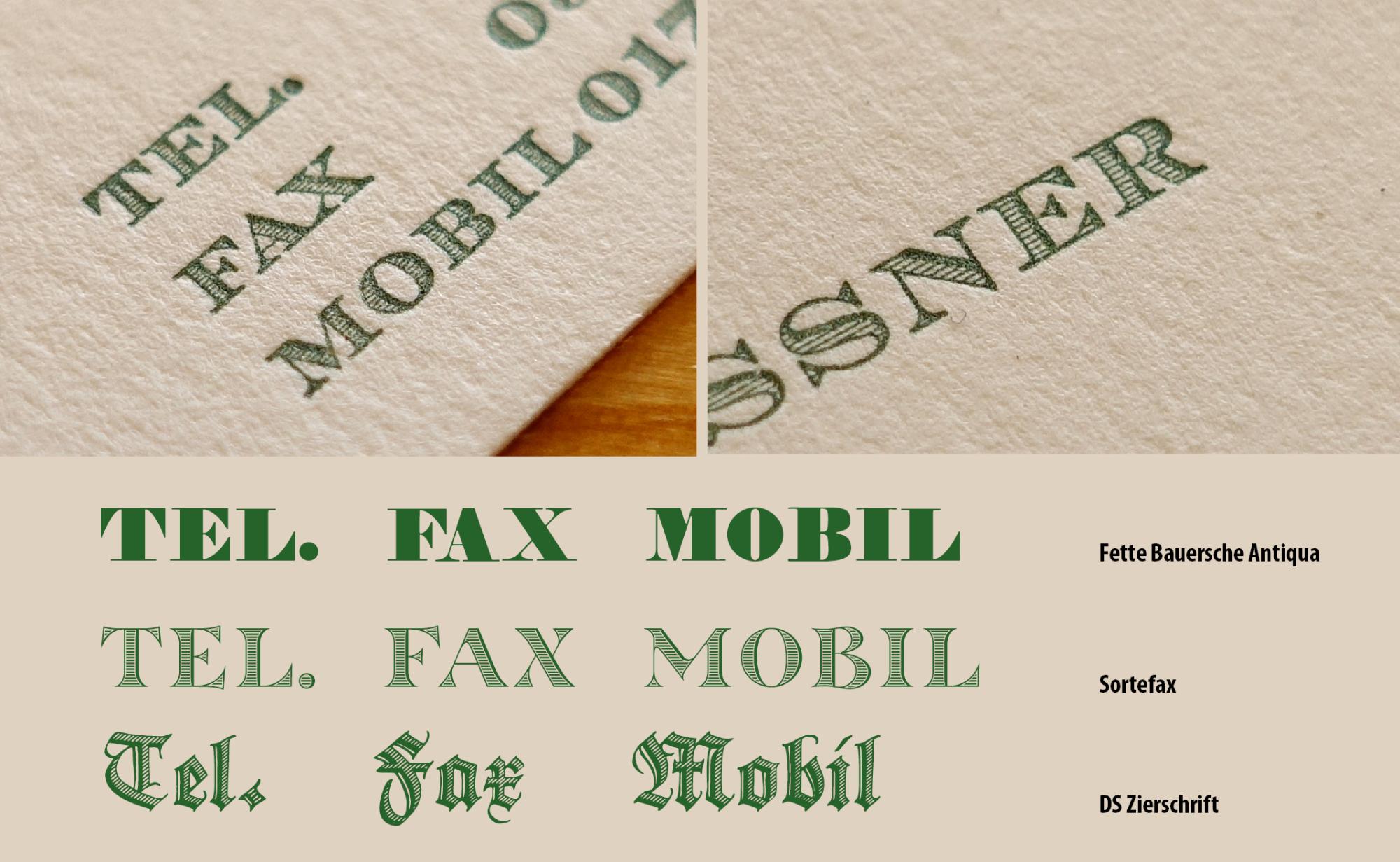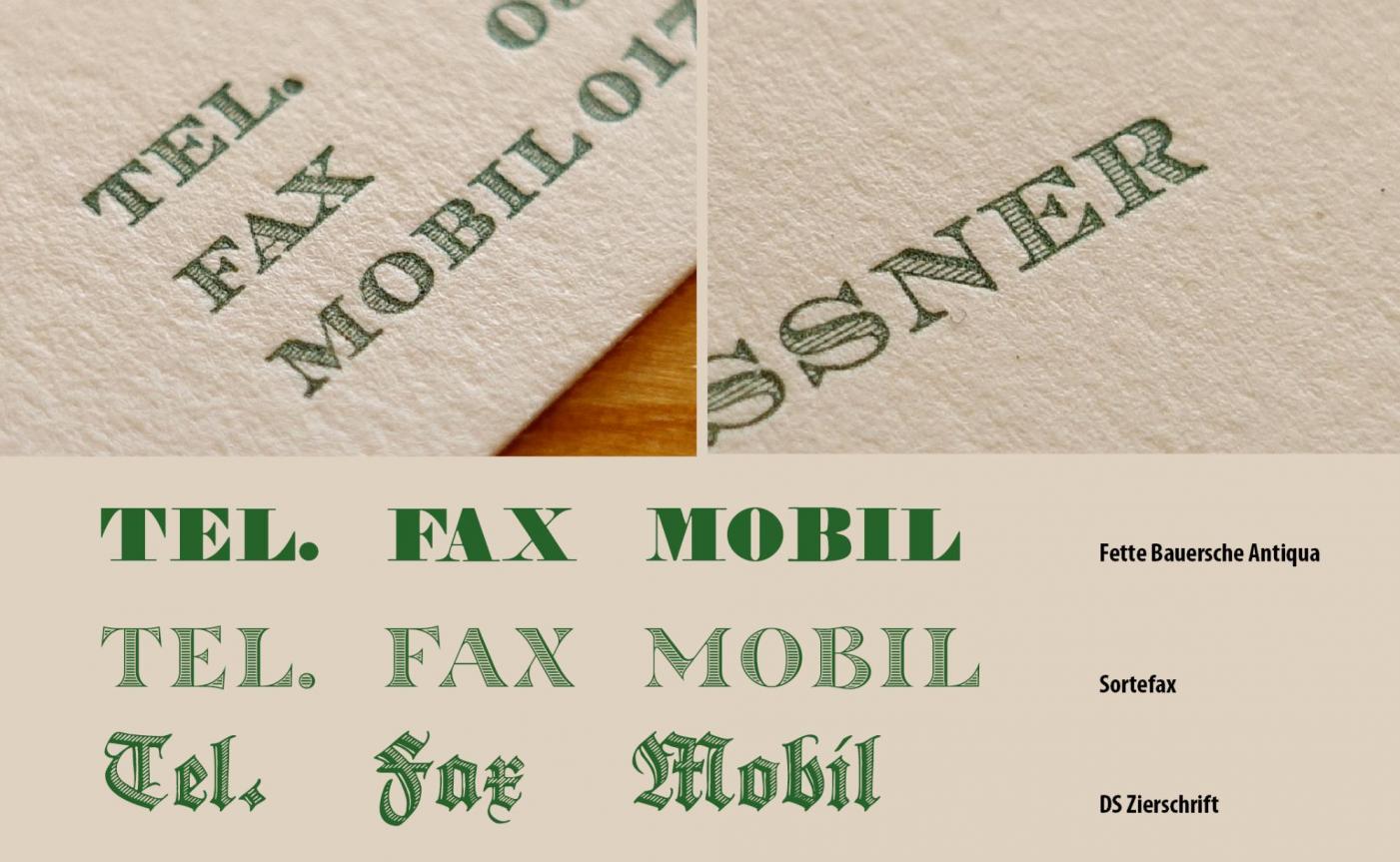
Namen alter „Fat-Face-Schriften“ (19. Jh.) mit Schraffur gesucht
Ich suche den Namen einer Schrift, so einer „klassischen, fetten Dollar-Noten-Schrift“, aber mit Schraffur. Ich hatte vor vielen Jahren einmal eine Visitenkarte erhalten und darauf war eine solche in Bleisatz zu sehen (und hat mich nachhaltig beeindruckt).
Nun habe ich bis zur Verzweiflung gestöbert, ob es denn so etwas als Font gibt, aber so richtig ergiebig war das noch nicht. 😢 Ihr seht oben, was ich denn als „ähnliches“ bisher so gefunden habe* – so etwa in die Richtung soll es gehen.
Meine Fragen lauten also:
1. Kennt zufällig jemand den Namen der auf der Visitenkarte verwendete Schrift in Blei?
2. Kennt jemand weitere/ähnliche Schriften mit Schraffur beim Namen in Blei?
3. Kennt jemand Fonts mit Schraffur, bevorzug diese „superfetten“ aus dem 19. Jh.? (Aber sie müssen halt „anmutig“ und „echt“ und „warm“ aussehen – keine ulkigen Spielereien oder welche wo einfach steril wirkende Striche innerhalb der Glyphen reingezogen wurden. Das ganze muss schon Qualität haben.)
4. Bonusfrage: Kennt jemand eine Font-Library wo man mal nach Schraffur (hatching, carving, woodcutting, o.ä.) filtern kann? Ich glaub langsam ich hab Tomaten auf den Augen … 🍅🍅
*= Ja, die Fette Bauersche Antiqua ist die von Catfonts. 😁
Und wie aus dem dankenswerterweise verlinkten Handbuch der Schriftarten zu entnehmen ist, laufen solche Schriften auch gern unter „Kartenschrift“ oder „Magnaten-Schrift“. Auch die Azuree spielt in dieser Kategorie. Zu den anderen interessanten Kandidaten aus dem Buch konnte ich auf die Schnelle keinen entsprechende Variante als Font finden.
Sidenote:
Langsam beginne ich zu glauben, dass sich der Herr damals für die Visitenkarte ein Klischee hat machen lassen, mit der Chevalier als Font, denn auf der Karte ist ein passend gestaltetes „@“ mit in der E-Mail-Adresse – und ich bezweifle, dass es das im Bleisatz so damals gab. 😁
kleiner nachtrag: eric van blokland hat sich dem thema »schrift auf dollar-noten« mit seiner federal gewidmet. perfekt mit bevel, verschiedenen schraffuren (und in verschiedenen optischen größen) sowie schatten. noch mehr dollar bill geht nicht!
Muss bloß ehrlich sagen, dass mir die Federal eher „künstlich grungy“ vorkommt, nicht „edel“.  Durch den Eindruck, dass die Schraffuren so stark auf dem Papier ausbluten, kann der Font eigentlich fast nur in kleineren Schriftgrößen wirken – größer sieht ja dann unnatürlich aus. Auch die verschiedenen optischen Größen helfen da nicht, denn der Strichstärkenkontrast von Buchstabe zu Schraffierung stimmt einfach trotzdem nicht.  (Hat aber dennoch ein Lob verdient, so einen Font hergestellt zu haben. 😉)
Muss bloß ehrlich sagen, dass mir die Federal eher „künstlich grungy“ vorkommt, nicht „edel“
da hast du schon recht. so richtig kitschig amerikanisch alt halt. für edel gibt’s ja die chevalier.